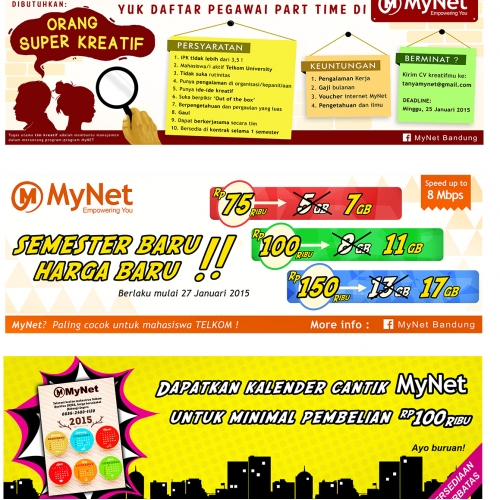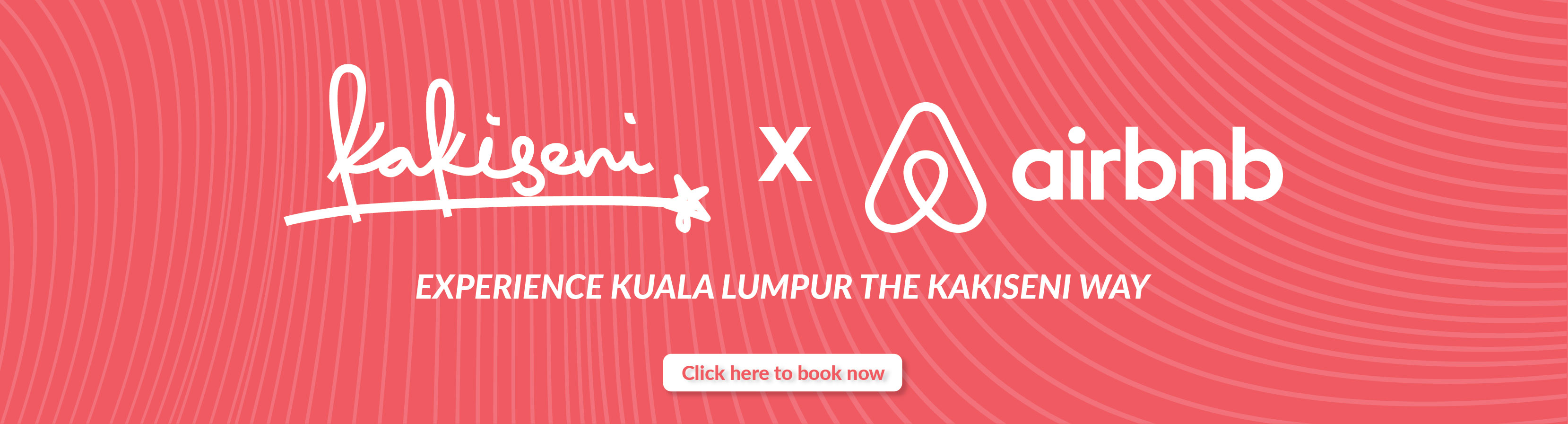
Font dibawah ini merupakan pilihan terbaik yang akan menjadikan desain anda terlihat menarik dan elegan.
Font cantik untuk banner.
Setelah saya kumpulkan dari beberapa sumber market font ternama.
Font terbaik untuk desain gratis.
Kini saya akan membagikan sebuah tulisan dengan tema serupa namun berbeda judul.
Rekan pekerja grafis di manapun anda berada dan sedang membaca tulisan ini beberapa pekan lalu ayuprint membuat sebuah postingan tentang daftar font font untuk desain undangan pernikahan dan beberapa font dengan tema judul judul film terpopuler.
Berikut adalah 30 lebih font gratis terbaik untuk desain grafis anda bisa mendownload dan menggunakan font dibawah ini untuk kebutuhan desain grafis anda.
Apalagi posternya tentang hal yang menegangkan atau peringatan.
Dengan 430 simbol yang dicantumkan script ini merupakan tambahan sempurna pada koleksimu.
Download bungasai font free for commercial use bungasai diambil dari bahasa banjar bungasai yang digunakan untuk memanggil seseorang yang cantik atau tampan bermaksud memuji.
Bisa dijadikan perpaduan baru untuk desain poster sobat.
Berbagai kebutuhan desain sangat membutuhkan font baik itu desain logo banner undangan brosur menu makanan promo desain web dan masih banyak lagi.
Berdasarkan garis dan bentuk geometris font modern bersih jelas dan mudah dibaca.
Font fot ini sangat berguna untuk keperluan design grafis seperti membuat logo banner text art dll juga untuk keperluan mendesign sebuah web.
Ditambah dengan kreatifitas memutar dan memisahkan detailnya font dapat memiliki nuansa keren dan kontemporer.
Berikut ini adalah 50 font yang akan memberikan desain anda tampilan baru.
Ada beberapa rekomendasi font yang cocok digunakan oleh para desainer.